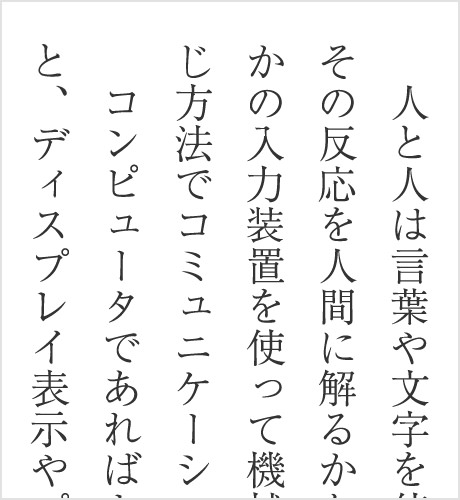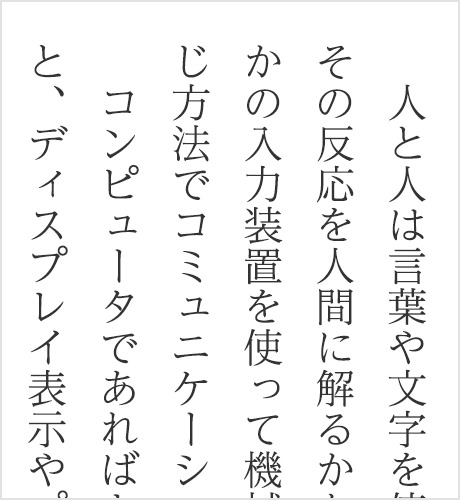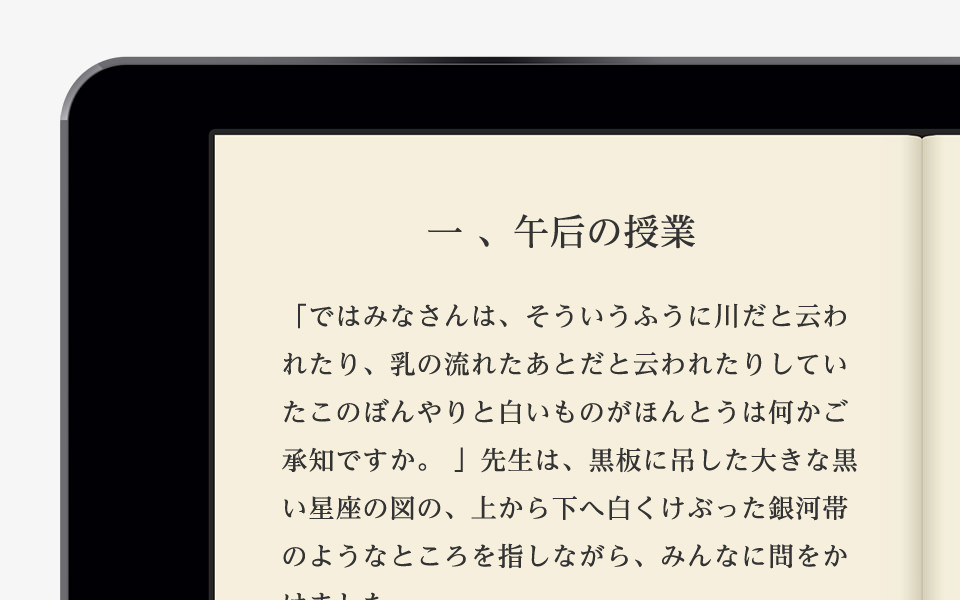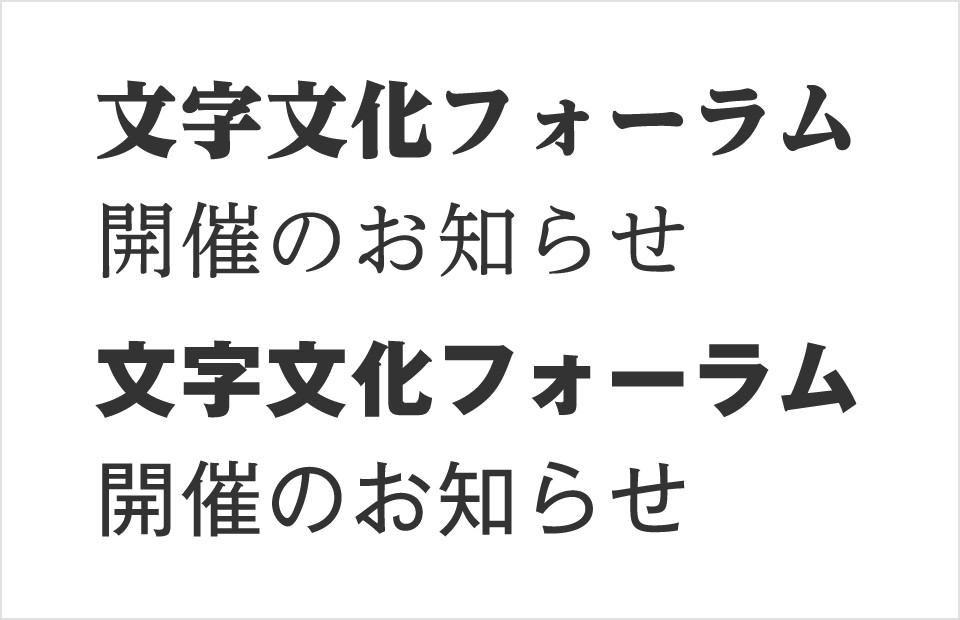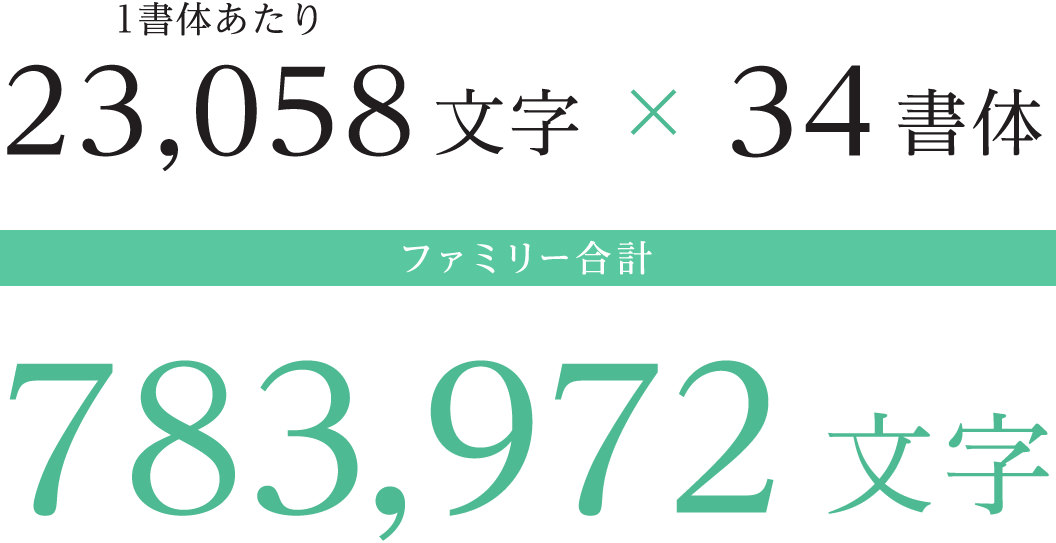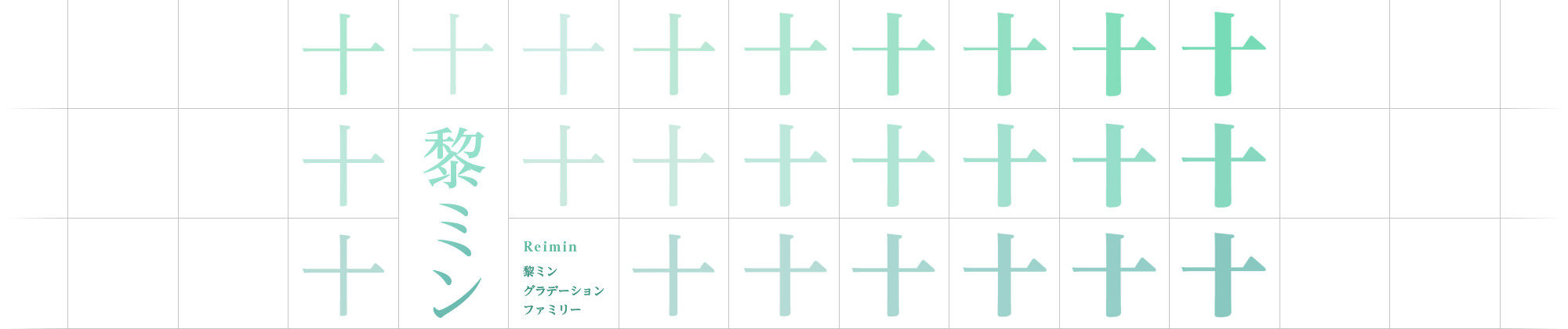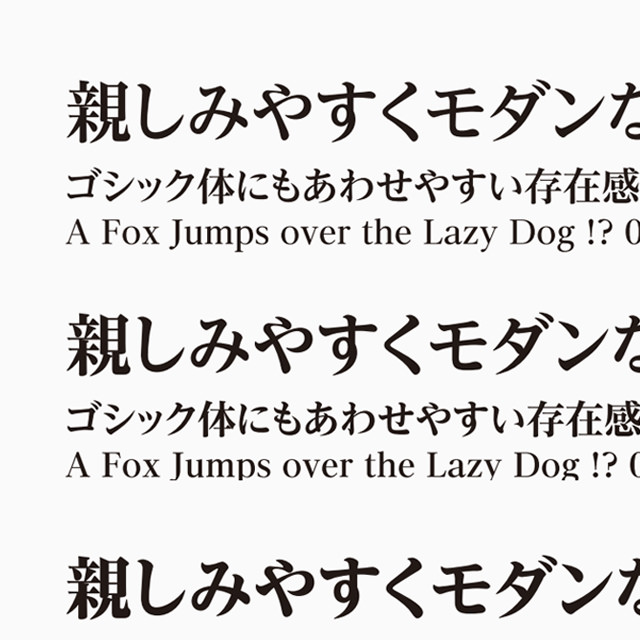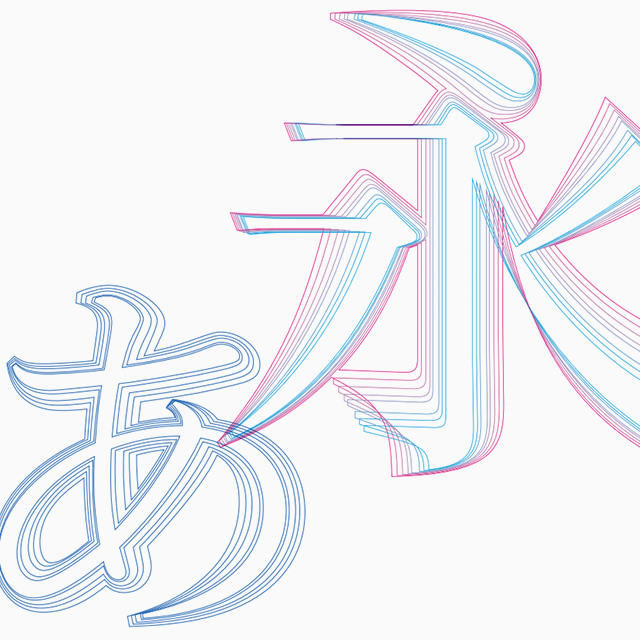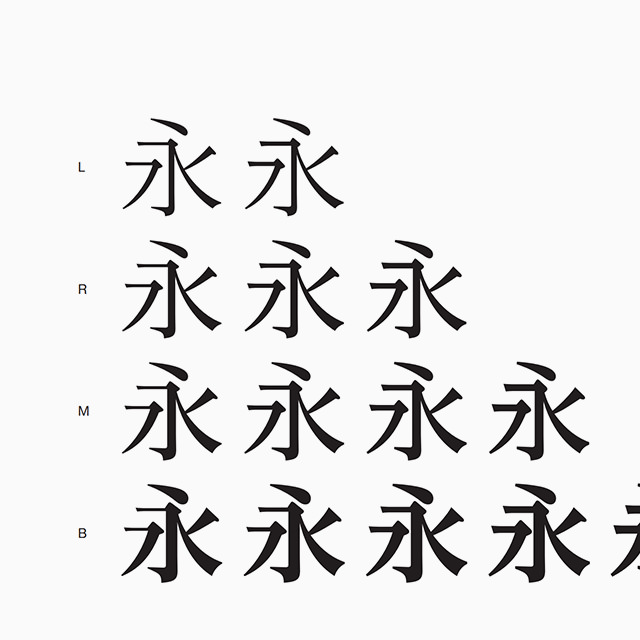
クセのないニュートラルな明朝体「黎ミン」
34書体もの多彩なバリエーションを持つ黎ミングラデーションファミリー。
縦画と横画の太さを組み合わせることで、どんな目的にも使える柔軟性を実現しています。
明朝体の可能性を広げる横画のバリエーション
「黎ミングラデーションファミリー」は、「黎ミン」をベースに、横画の太さを段階的に変化させたY0(Y表示なし)~Y40の5つのバリエーションと、8つのファミリーの計34書体で構成されています。従来の、おもに縦画が変化するウエイトという軸に、横画の太さという軸が加わり、幅広い表現や繊細な選択が可能になりました。ここでは全34書体を目的別の4つのグループに分類して紹介します。
2012年、世界で最も文字数の多い書体ファミリーに認定されました。
今回記録として認定されたのは、ウエイト間で共通したグリフや重複するものを除いた748,811文字で、書体に関する記録は世界初となります。(Adobeの文字セット規格で最も文字数の多いAdobe-Japan 1-6に対応)
黎ミンの特徴
親しみやすく、クリアなイメージ
オールドスタイルの「秀英明朝」や、スタンダードな「リュウミン」は、明朝体らしさの中にクラシカルな印象も持ちあわせています。それに対して、モダンなデザインの「黎ミン」は、クリアなイメージで文字を見せたいときに最適です。
見やすくて、横組みも美しい。
字面が揃い、フトコロの広いモダンな明朝体である「黎ミン」は、縦組みだけではなく、横組みでもラインや黒みの揃った美しい組みとすぐれた可読性を発揮します。
ゴシック体にも負けない力強さ
「黎ミンY30」「黎ミンY40」のように横画の太い書体なら、これまでの明朝体ではできなかった、ゴシック体に負けない強さとインパクトのある表現ができます。